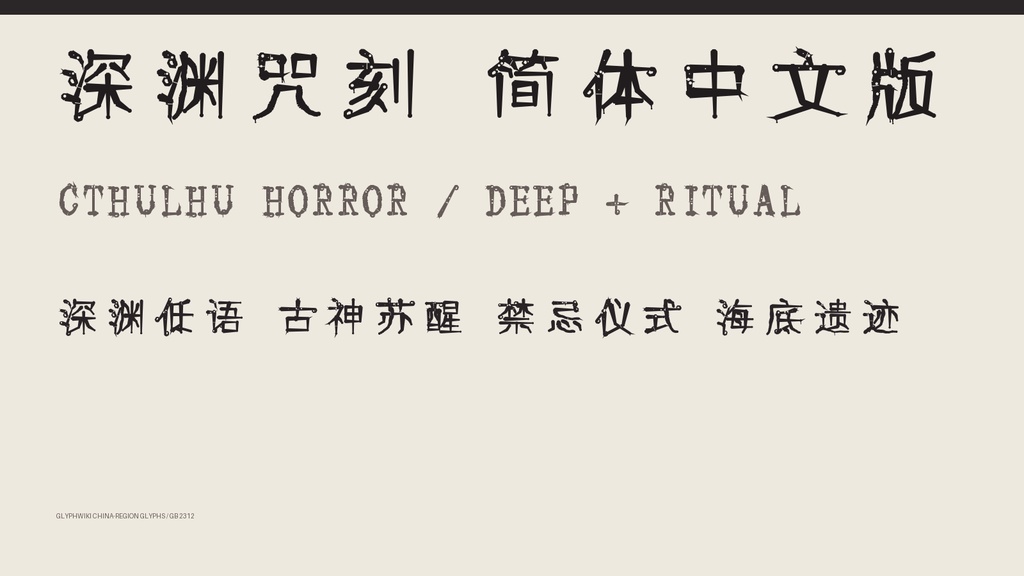
深渊咒刻 SC|简体字6,763字・2款字体
【深渊咒刻 SC / SHINEN JUKOKU SC】 文字仿佛从深海遗迹中苏醒,触手、吸盘、眼睛与伤痕缠绕在笔画之间。 这是一套克苏鲁神话风格的简体中文恐怖展示字体。 Deep 呈现沉入海底的有机轮廓,Ritual 则强化禁忌仪式与咒刻般的异形细节。 ■ 价格 1,680日元 ■ 内含字体 ・Deep:深海触手与有机侵蚀风格 ・Ritual:咒文、祭仪与刻印感更强的版本 ■ 格式 TrueType(TTF)2款 / Windows・macOS ■ 收录 每款共7,542个字码(包含空格) GB 2312 全部汉字:6,763字 拉丁字母、数字、半角与全角符号:779个 ■ 特点 ・触手、吸盘、异眼与裂伤般的笔画装饰 ・两种不同强度的克苏鲁恐怖表现 ・汉字、英文字母、数字和符号采用统一的异形规则 ・大字号下可清楚呈现细节 ■ 推荐用途 克苏鲁TRPG、恐怖游戏、怪奇电影标题、小说封面、音乐封面、海报、直播画面、邪教与禁忌仪式题材 ■ 使用许可 可用于个人及商业项目。可用于标志、视频、游戏、印刷品、直播素材、同人及商业作品。 无需署名。禁止重新分发、共享或转售字体文件。 详细条款请查看ZIP内的使用许可。 ※含有细小触手与裂纹细节,推荐用于28px以上的标题。